Els tipus de lletra més populars per al disseny web
Quan parlem de disseny web, ens referim a l’estructuració del contingut, a l’ús adequat de les imatges i a la importància d’escollir una o diverses bones tipografies que reforcin el disseny que volem transmetre.
Sens dubte, la plataforma de referència a l’hora de triar tipografies per a la web és google fonts: https://fonts.google.com/
Google Fonts per triar la teva tipografia en el disseny web
Fa uns anys, com ja sabreu, el més habitual quan dissenyàvem una pàgina web era utilitzar les tipografies de sistema, ja que la majoria de navegadors no permetien fer servir tipografies externes.
Des de fa temps, però, amb els navegadors actualitzats, tenim centenars de tipografies a l’abast i, amb l’arribada de google fonts, encara és més senzill.
Les tipografies més populars segons Google Fonts
A continuació, compartim el rànquing de les 5 tipografies més utilitzades segons Google Fonts. Aquesta classificació es basa en el nombre de sol·licituds que rep cada tipografia.
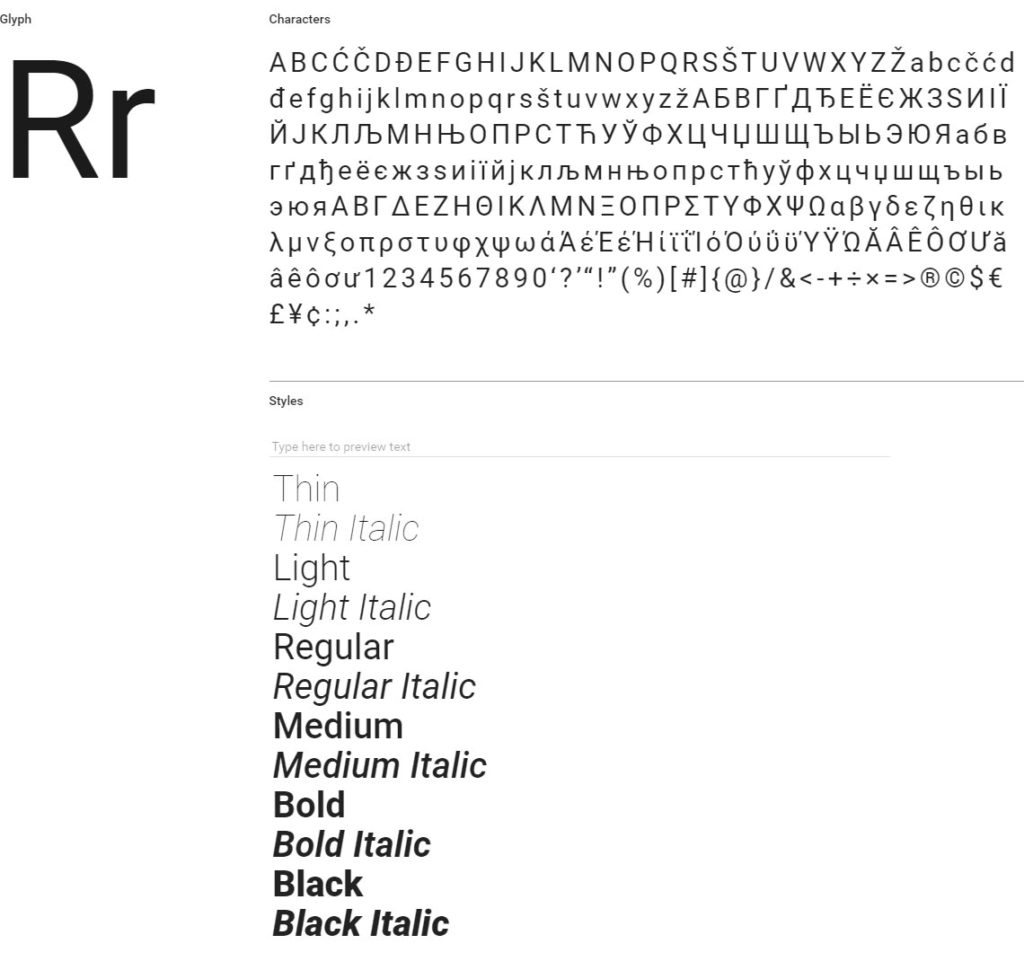
1. Roboto
roboto
Dissenyada per Christian Robertson, és una tipografia mecànica i geomètrica. Es fa servir en ni més ni menys que 32.600 milions de llocs web.
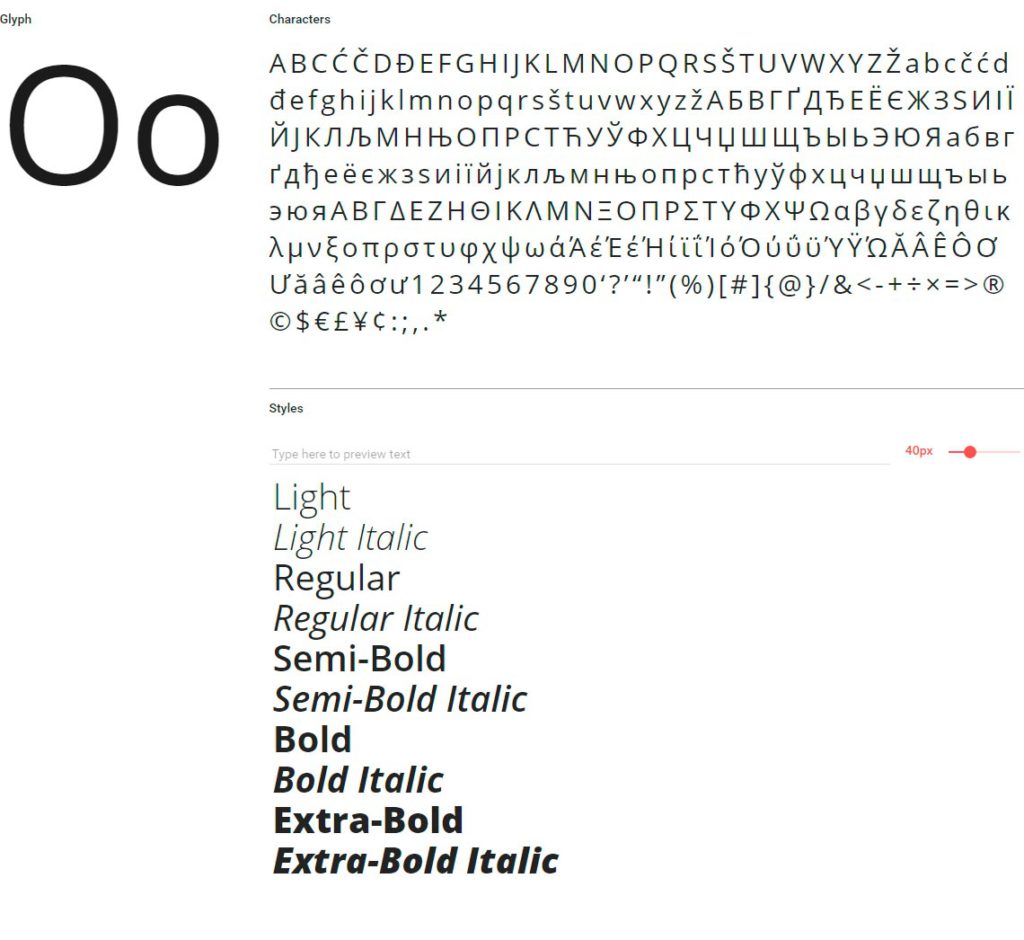
2. Open Sans
open sans
En segon lloc trobem Open Sans, una tipografia creada per Steve Matteson. Ha estat optimitzada per garantir una lectura excel·lent tant en format web com imprès. Amb Open Sans s’han dissenyat 28.000 milions de pàgines web. Nosaltres l’hem utilitzada en diversos projectes i, sincerament, és una de les nostres preferides.
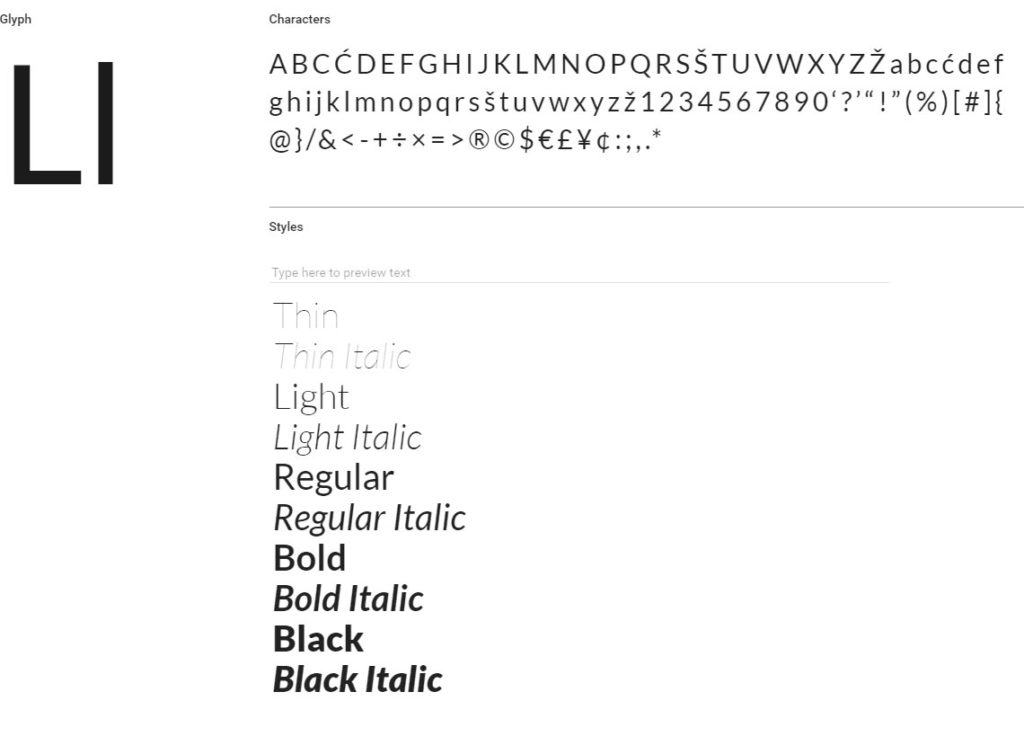
3. Lato
lato
Lato, dissenyada per Łukasz Dziedzic, és una sans serif utilitzada en 6.980 milions de llocs web. Ofereix una àmplia gamma de pesos, des d’una negreta molt marcada fins a un pes ultralleuger. Aquesta tipografia em porta records especials, ja que si no vaig errat, va ser una de les primeres que vaig fer servir amb Google Fonts, deixant enrere la clàssica Arial.
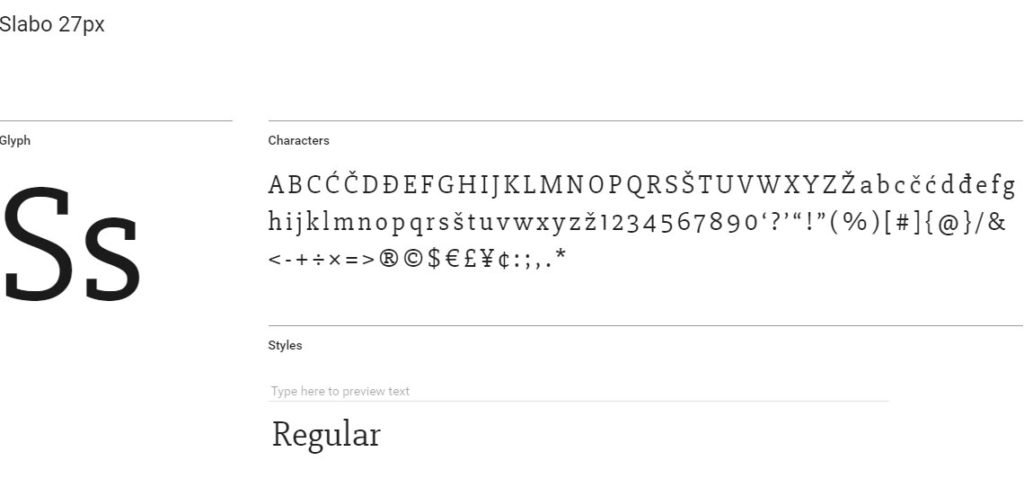
4. Slabo 27px
slabo
Dissenyada per John Hudson, Slabo 27px és una tipografia força singular. Es tracta d’una tipografia pensada específicament per utilitzar-se a la mida concreta de 27px. Està orientada a entorns digitals, com el disseny web i el màrqueting online. A més, també existeix la Slabo 13px. El fet d’estar creada per a una mida concreta permet obtenir un resultat visual impecable.